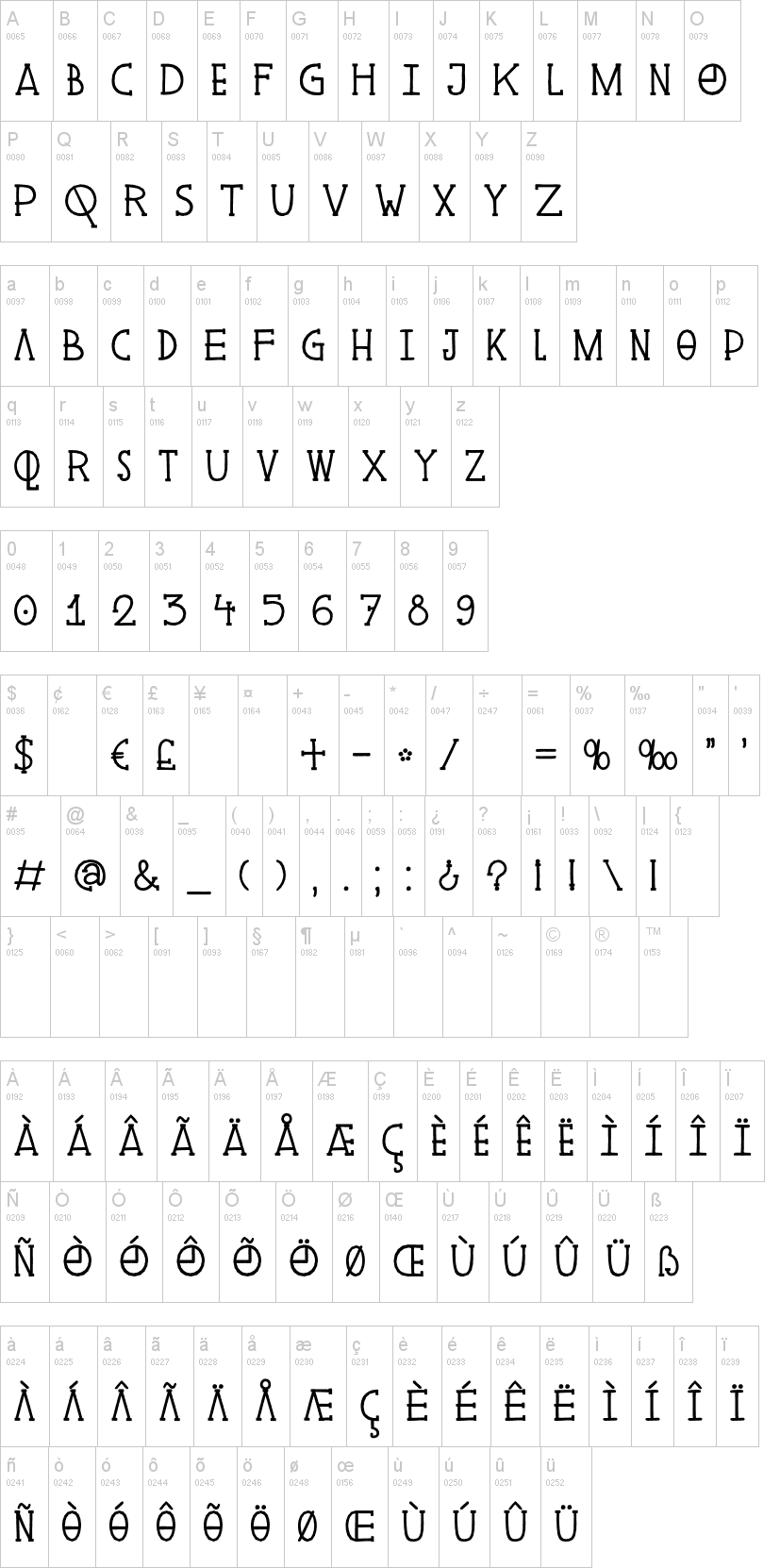
DK Pingo
DK Pingo 是一款由汉堡设计师Hanneke Classen创建的手写风格字体。这款字体具有欢快和轻松的感觉,同时呈现出一种独特的儿童氛围。DK Pingo 字体包含了大写和小写字母,数字和标点符号,支持英语和西欧语言。这款字体可用于多种场合,如海报、卡片、标志、广告等,给人们带来轻松温暖的感觉。
DK Pingo是一款非常不错的手写艺术字体,具有很好的视觉感,适合于文化类的宣传设计、商业类品牌的广告和产品包装设计以及个性化文字排版等较多场景。